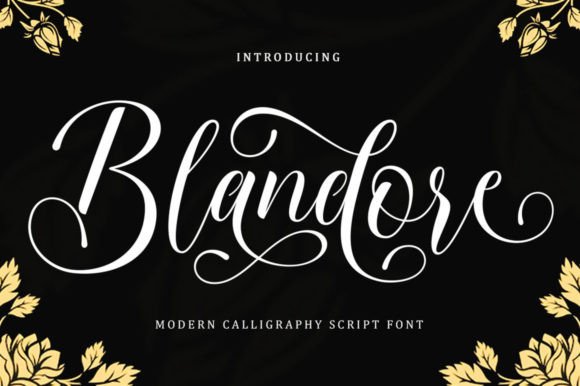
Blandore
Encontrar los elementos de diseño adecuados puede ser un desafío, pero Blandore ofrece una colección excepcional que eleva tu trabajo al instante.
Ya sea que estés creando productos POD (impresión bajo demanda), invitaciones de boda o gráficos para redes sociales, Blandore es una opción ideal.